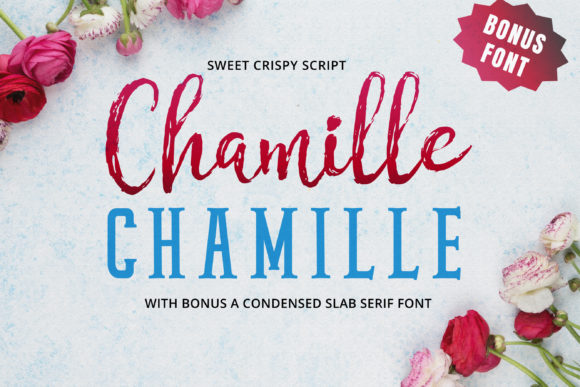
Chamille Script
Якщо ви шукаєте високоякісні ресурси, такі як Chamille Script, цей преміум-пакет є фантастичним вибором для ваших творчих проектів.
Створений з високою точністю, Chamille Script забезпечує чисті вектори, плавну типографіку та комерційну ліцензію для вашого спокою.
Незалежно від того, чи створюєте ви продукти POD (друк на вимогу), весільні запрошення або графіку для соціальних мереж, Chamille Script стане ідеальним вибором.